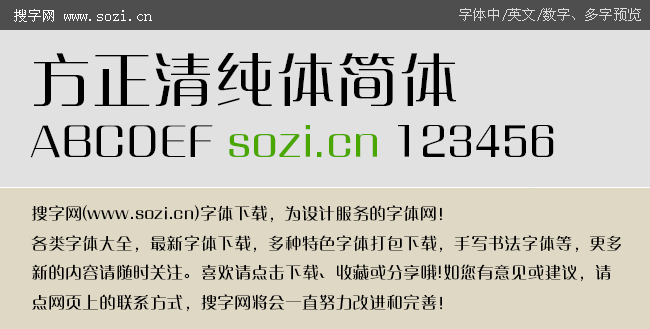
方正清純體簡(jiǎn)體
搜字網(wǎng)提供一款方正清純體簡(jiǎn)體中文藝術(shù)字體下載,方正清純體筆畫(huà)粗細(xì)對(duì)比明顯,橫細(xì)豎粗,筆形富于變化,整體給人清新、靈動(dòng)、優(yōu)美、圓潤(rùn)之感,適合應(yīng)用于廣告設(shè)計(jì)、名片設(shè)計(jì)、包裝印刷、兒童產(chǎn)品設(shè)計(jì)等應(yīng)用。